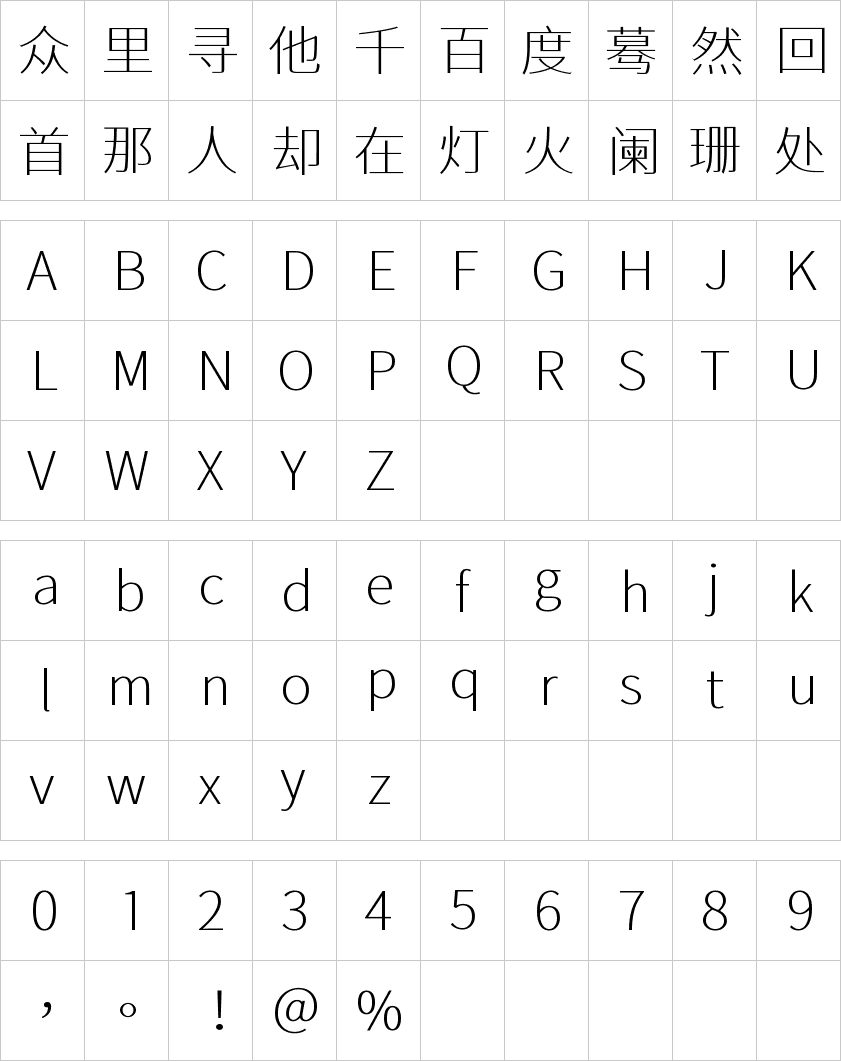
江城正义体
江城正义体是基于思源黑体改造,把思源黑体横向减细处理,纵向增粗处理,得到类似粗宋风格字体,这款字体削减了横笔的粗细,使字体看上去更具现代感。特别适合用于海报标题,LOGO等方面的设计。
这款字体跟日本设计师发布的源暎漫画体有点类似,但是江城正义体的横笔比源暎漫画体更细,看上去更有特色。另外,源暎漫画体是使用日本版的思源黑体改造的,所以对简体中文支持并不好,并且只有一个字重。而这款江城正义体则是基于中国版思源黑体改造,更符合中国大陆的习惯,基本上不缺字。并且还有5个字重。